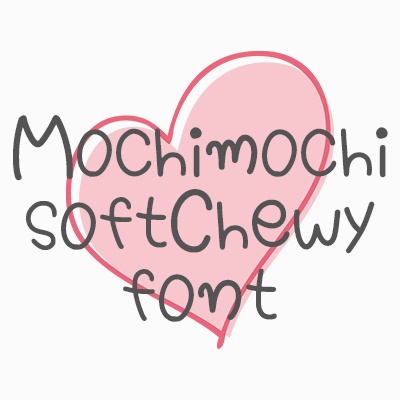
mochimochifontもちもちフォントダウンロード商品¥ 150カートに入れるギフトとして贈る「ギフトとして贈る」とは女の子の可愛い手書き風フォントです。 基本的な記号と アルファベットの大文字と小文字を使用できます。 海外のリスナー様にむけた動画やサムネイルなどにおすすめです。 可愛い作品をつくる少しのお手伝いが出来たら嬉しいです! フォントを使用したものを商用利用していただくことは可能です。 フォント本体そのままの販売は不可です。 mochimochifontFANBOX開設中